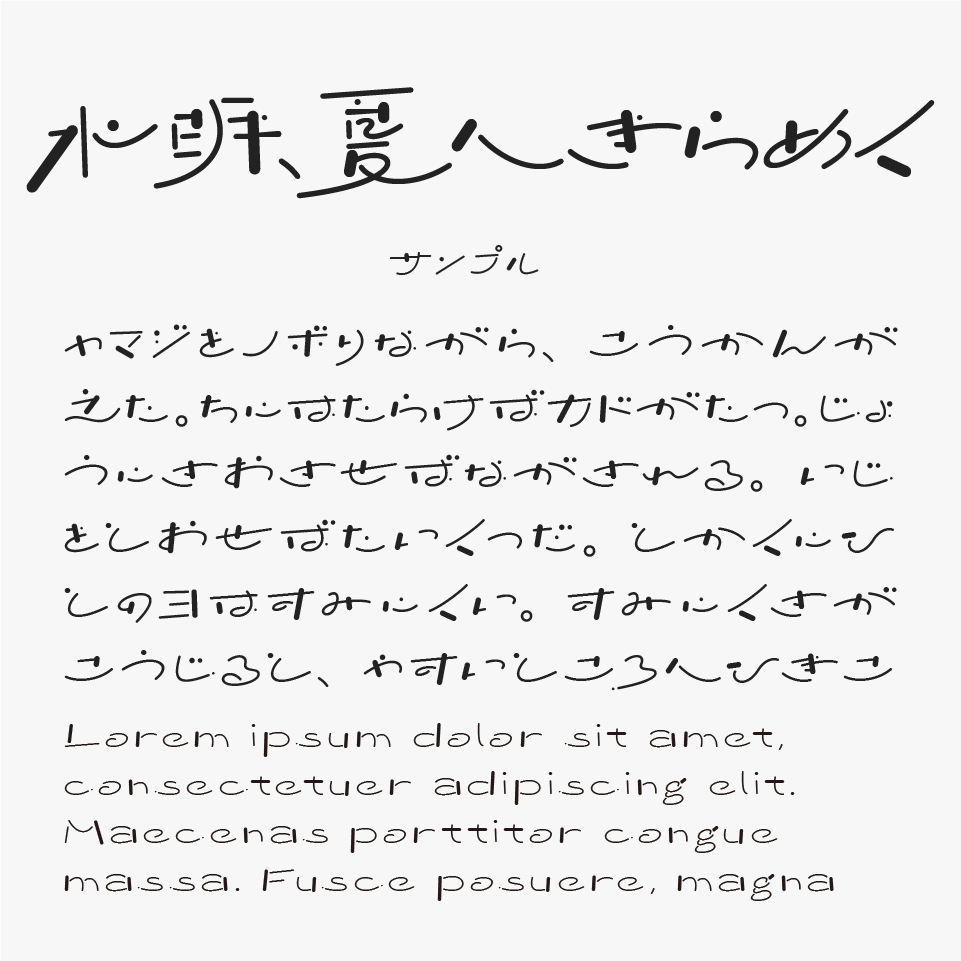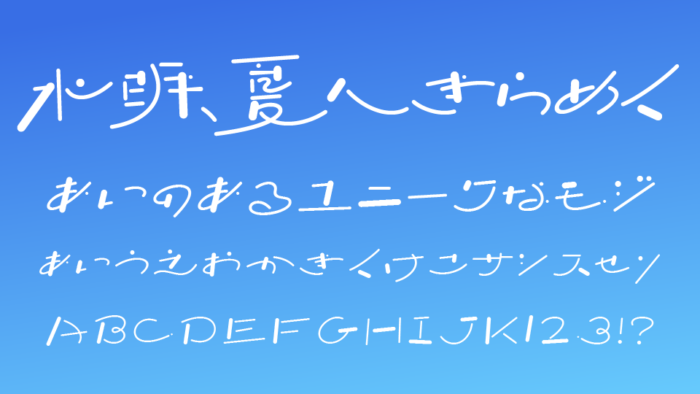
水明、夏へきらめくフォントは、細く軽やかな線で綴られた、まるでノートの端に書き留めたような手書きフォントです。
「春から初夏にかけての、きらびやかで爽やかなイメージを表現」して制作されたフォントは、とっても軽やかさで夏の涼しさを感じさせられるようなステキなフォントです。
【Free版】にはひらがな・標準ラテン文字(大文字のみ)・数字・一部記号・漢字3文字(水明夏)が収録されています。